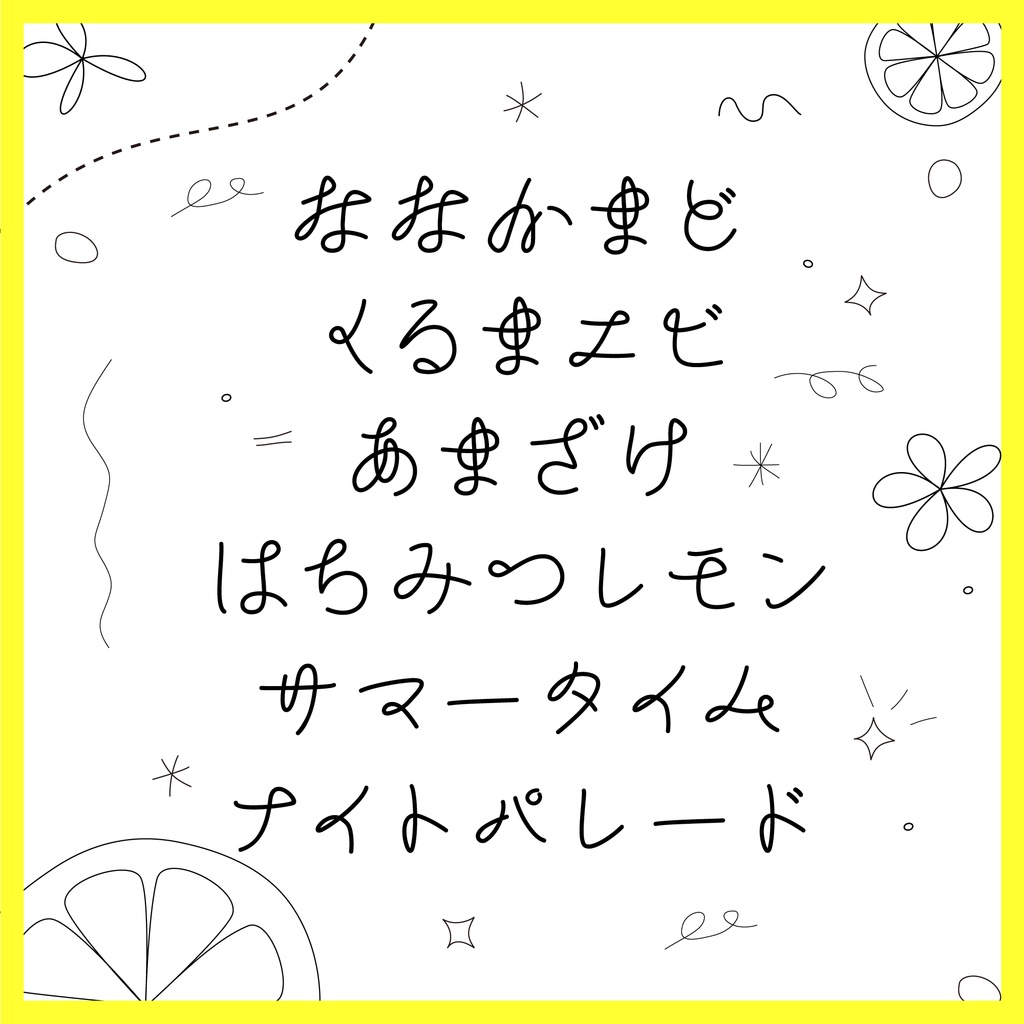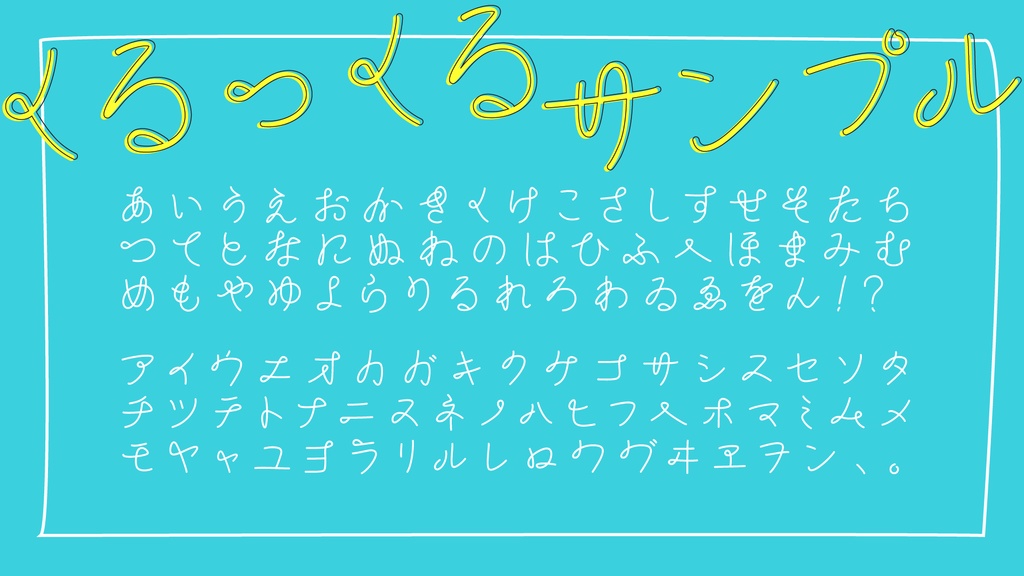
くるっくる【手書き風フォント】
※フォント形式はttfです ■書体概要 「くるっくる」作者の手書きの文字の独自の癖をリファレンスに出来上がったやわらかい手書き風の書体です。線の止めやハネが曖昧になりつつも流れるように「くるっ」と旋回してできあがった仮名のかわいさに注目! ■収録漢字 ひらがな・カタカナ、一部役物(、。・!?) ■ご利用にあたり 文字魚/Typographishのフォントデータ(以下、本ソフトウェア)は本契約に定める条件でご購入者様に使用する権利を許諾します。本ソフトウェアの著作権その他一切の権利は文字魚/Typographishに帰属します。 使用条件 1)購入者は本ソフトウェアを、本人が使用する1台までのコンピューターにインストールして使用することができます。事務所など複数人で使用する場合、コンピューターの台数分のライセンスをご購入ください。 2)印刷物に使用できます。(書籍・ポスター・看板など) 3)立体制作物に使用できます。(Tシャツ・雑貨・記事など) 4)放送・映像やWEBの制作物でアウトライン化または画像化した上で使用できます。(TV・CM・映画・DVD・ゲーム・アプリ・WEBサービス・電子書籍・動画配信・SNSなど) 5*)タイトルデザイン・ロゴマークの作成に使用できます。(*商標登録は不可) 6)Canvaなどオンラインデザイン制作ツール上にフォントをアップロードして使用することがきでます。ただし使用者1名、PCまたはタブレットなど1台の使用に限ります。 禁止事項 1)本ソフトウェアを第三者に譲渡・貸与・配布・販売することはできません。 2)本ソフトウェアを元に新たな類似または同一のフォントデータを作成すること。 3)本ソフトウェアをWEBフォントとして使用すること。 4)本ソフトウェアをハードウェアに組み込みすること。 5)本ソフトウェアを使用して商標登録をすること。 免責事項 本ソフトウェアを使用して発生した如何なる問題についても、文字魚/Typographishは責任を負わないものとします。万一、本ソフトウェアが原因で使用者および第三者に損害を及ぼしてもすべて使用者が責任を負うものとします。 保証範囲 1)本ソフトウェアに著しい誤字などが発見された場合は、修正に努め修正アップデートの情報は販売ページで告知します。修正アップデートの追加料金は不要とします。 2)本ソフトウェアのインストールに伴う技術的なサポートはいたしません。 その他 上記に記載されていない条項に関しては、著作権法及び関連法規に従うものとします。 2025/05/21 Ver1.000 Copyright (c) 2025 Typographish All Rights Reserved.